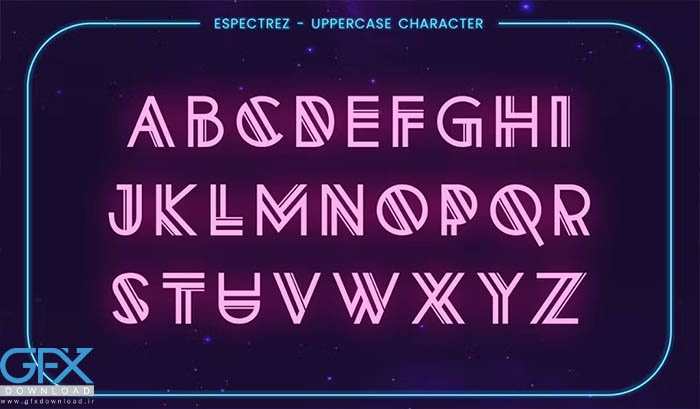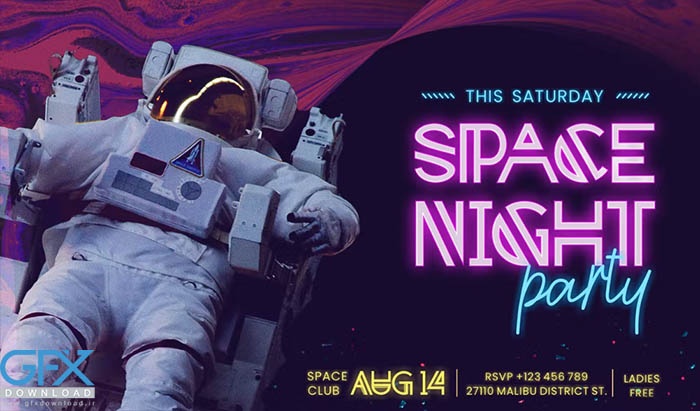
فونت رایگان نئونی ESPECTREZ
فونت نئونی ESPECTREZ
ESPECTREZ یک فونت انگلیسی منحصر به فرد است که از تابلوهای نئونی الهام گرفته شده است. فونت رایگان نئونی ESPECTREZ یک فونت sans serif allcaps است که از خطوط تشکیل شده است، ماهیت این فونت انگلیسی به صورت مدرن است، برای طرح های مدرن و مضمون کهکشانی یا آینده نگر بسیار خوب خواهد بود.